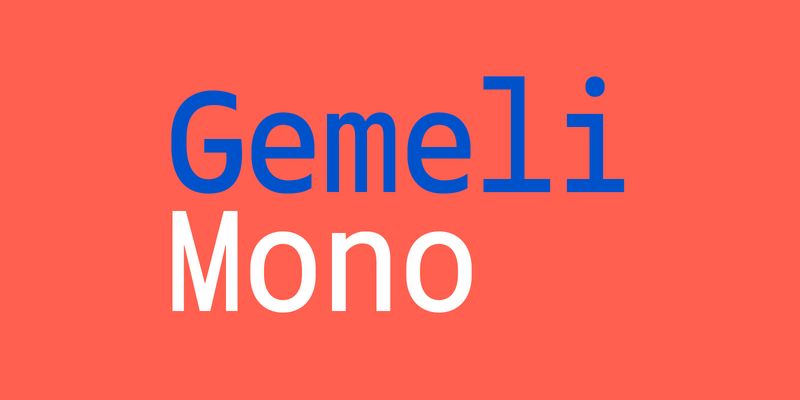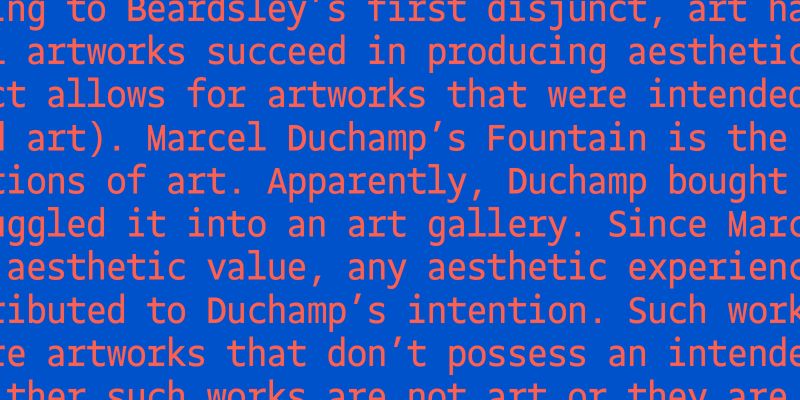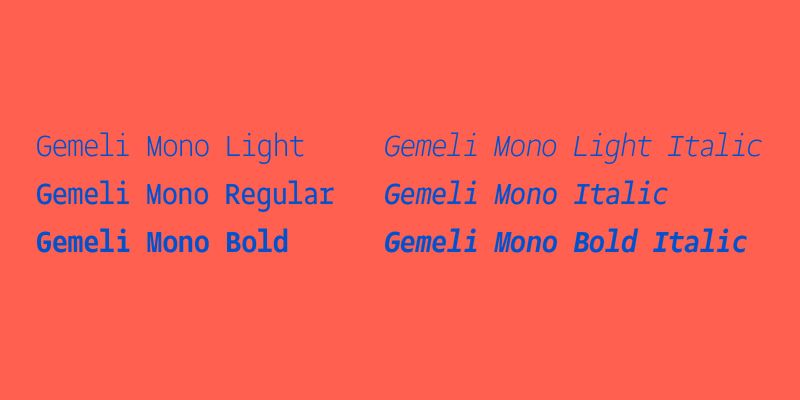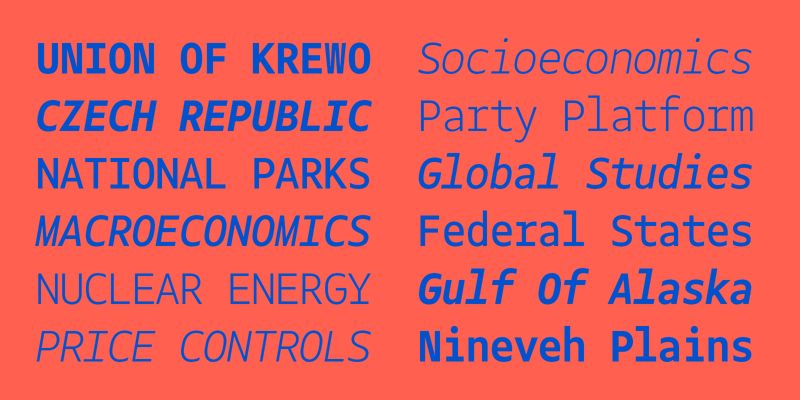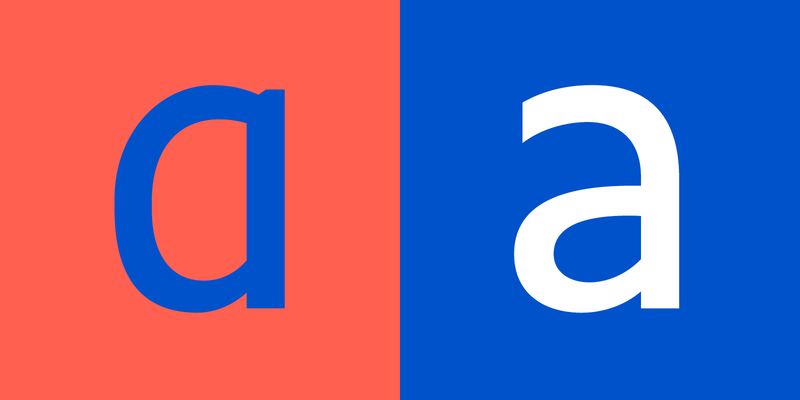
Gemeli er baseret på samme princip, nemlig menneskelige rammer, som sit modstykke Cogito, men skrifttypens lodrette streger giver den et skarpere, mekanisk udseende og en påfaldende anderledes personlighed.